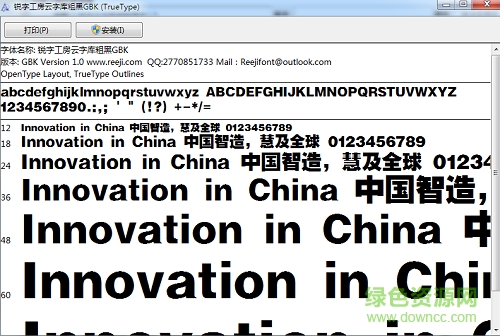
cloudheichaocugbk字體又叫銳字云字庫超粗黑體,是一款方頭方尾簡潔無裝飾的黑體字體,可以廣泛用于圖文排版、宣傳導(dǎo)語、品牌設(shè)計、文章標題等方面,需要的小伙伴快來下載吧!
筆畫超粗而有力,字形結(jié)構(gòu)嚴謹,樸素大方,穩(wěn)重醒目,特點是沒有襯線裝飾,字面呈正方形的粗壯字體,筆劃粗壯有力,撇捺等筆畫不尖,字形端莊,筆畫橫平豎直,全部一樣粗細,結(jié)構(gòu)醒目嚴密。方正、粗獷、樸素、橫豎筆形粗細視覺相等、黑白均勻,因此非常醒目,運用廣泛。